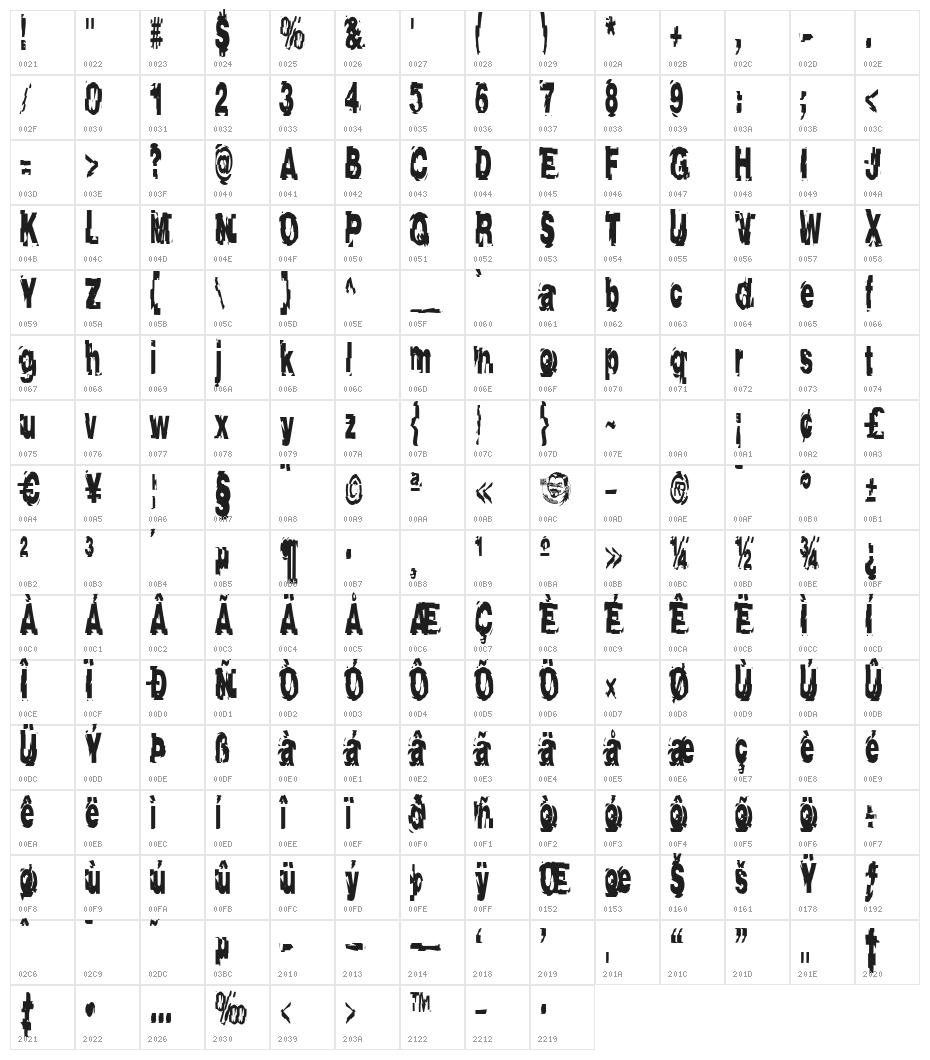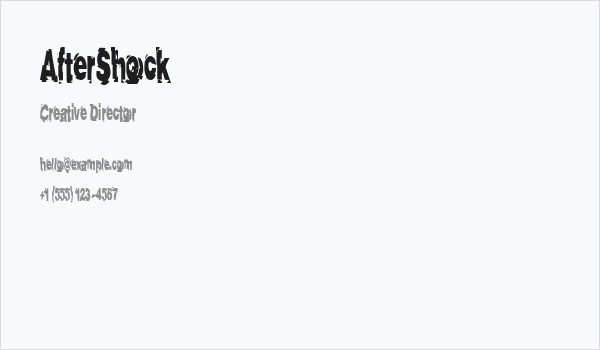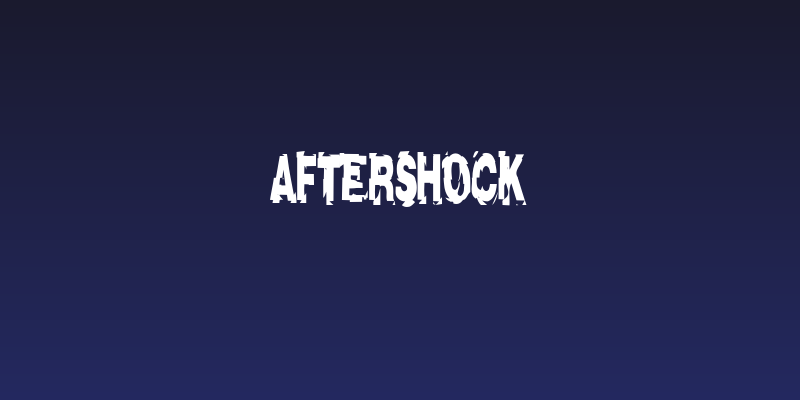
AfterShock Font
✎ Distorted Eroded
| Categorie | Distorted Eroded |
| Stile generale | Modern, Edgy |
| Progetti proposti | Ideal for music album covers, event posters, edgy branding, and any design needing a strong, impactful visual. |